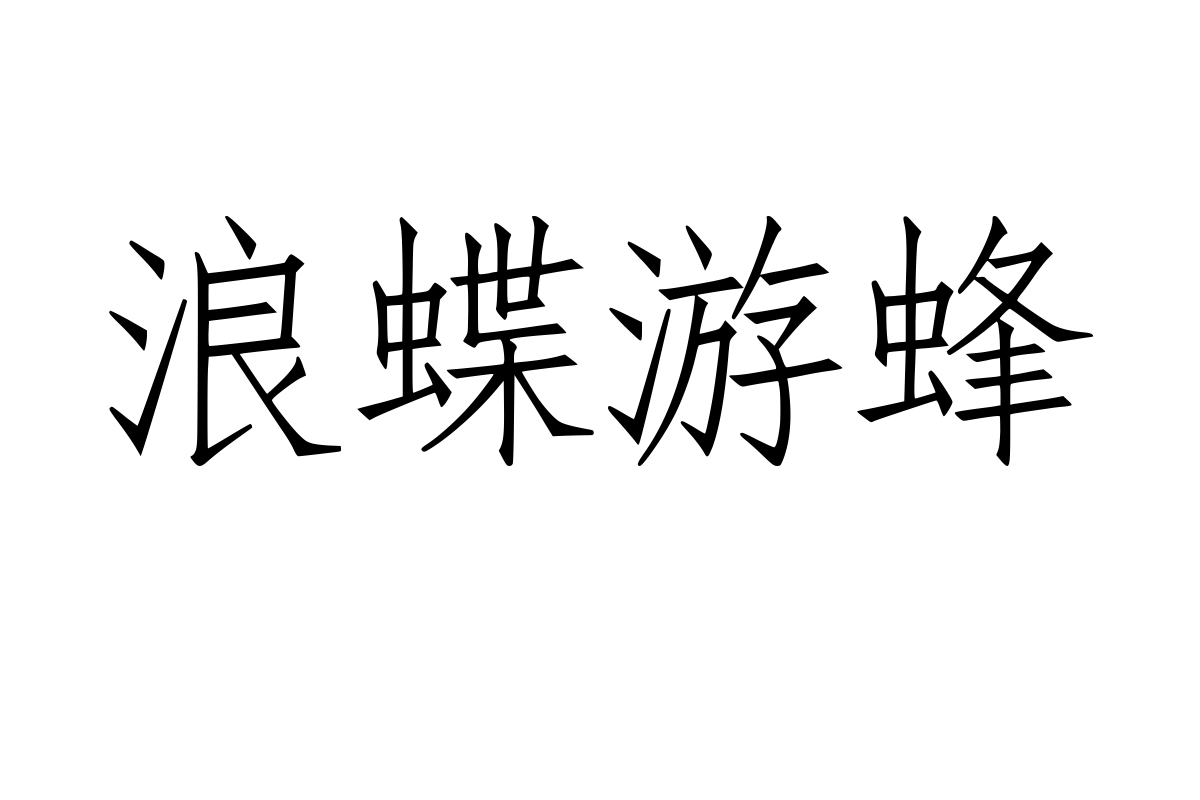
兰米仿宋体是一套由兰米公司设计的中文字体,具有独特的风格和特点。该字体以其清晰、易读的字形和优美的线条而受到广泛好评。兰米仿宋体在设计上采用了传统的仿宋体字形,但通过现代的设计手法和创新,使其更加符合现代人的审美需求。
兰米仿宋体的特点包括:
1. 字形清晰:兰米仿宋体的字形结构简洁明了,易于阅读,适合用于各种文字排版。
2. 线条优美:兰米仿宋体的线条流畅自然,给人以美的享受。
3. 适用范围广:兰米仿宋体适用于各种印刷品和电子媒体,如报纸、杂志、书籍、广告、网页等。
4. 可定制性强:兰米仿宋体支持多种字重和行距设置,用户可以根据自己的需求进行个性化定制。
总之,兰米仿宋体是一款优秀的中文字体,具有清晰的字形、优美的线条和广泛的适用性,能够满足各类文字排版的需求。